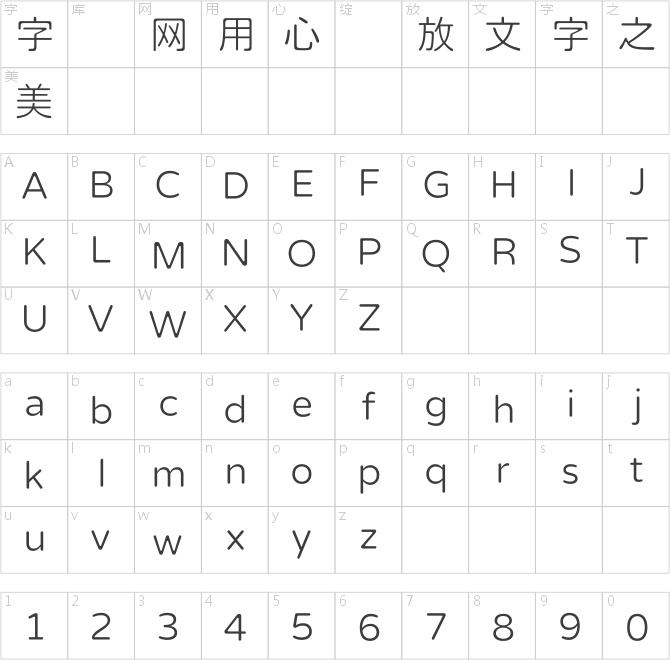
2020年3月14日,臺灣JustFont.com公開了一款圓體字體“粉圓字體”給大家免費商用。由于現(xiàn)階段可以免費商用的圓體字型十分少,所以這款字體十分受歡迎。而臺灣的設(shè)計師Max,把這款字體調(diào)整增加了字體,使得這款字體具有5字重, ExtraLight,Light,Regular,Medium, SemiBold,更方便設(shè)計師使用了。而Max把調(diào)整過的字體命名為假粉圓體。
由于假粉圓體是通過程序自動進行調(diào)整的,所以有可能存在某些字因為筆畫過粗而出現(xiàn)粘連,或者筆畫過細(xì)而消失。所以大家在使用時請檢查有沒有出現(xiàn)這樣的情況。如果有問題,可以向Max反映。